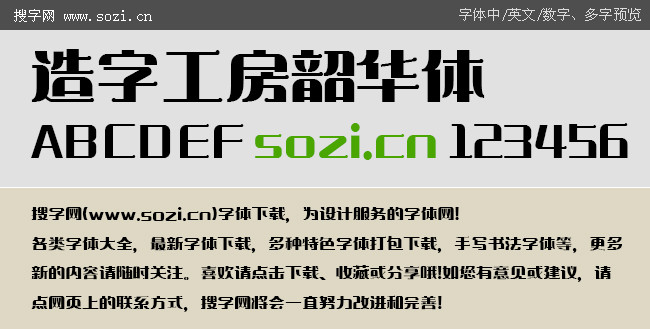
造字工房韶華體
搜字網(wǎng)給大家提供一款造字工房韶華體中文字體下載,,造字工房韶華體線條粗細(xì)適中,字形端正大方得體,整體效果出色,并且字庫(kù)完整,能夠適用于產(chǎn)品包裝、廣告宣傳、出版印刷、商標(biāo)用字、商業(yè)網(wǎng)站、影視影像視頻、書籍出版印刷等應(yīng)用。(本字體為個(gè)人非商用版,如需要商用請(qǐng)聯(lián)系官方購(gòu)買版權(quán))